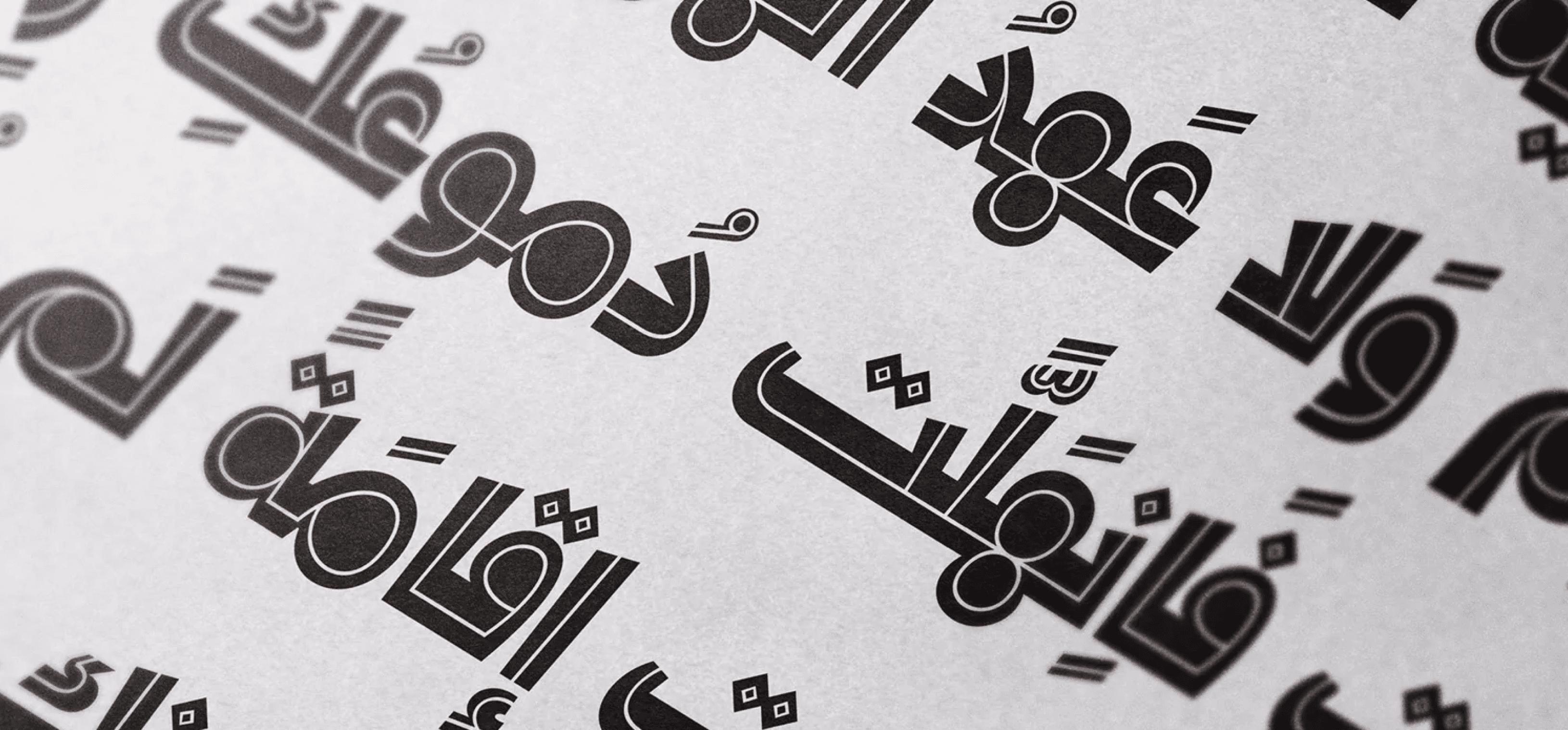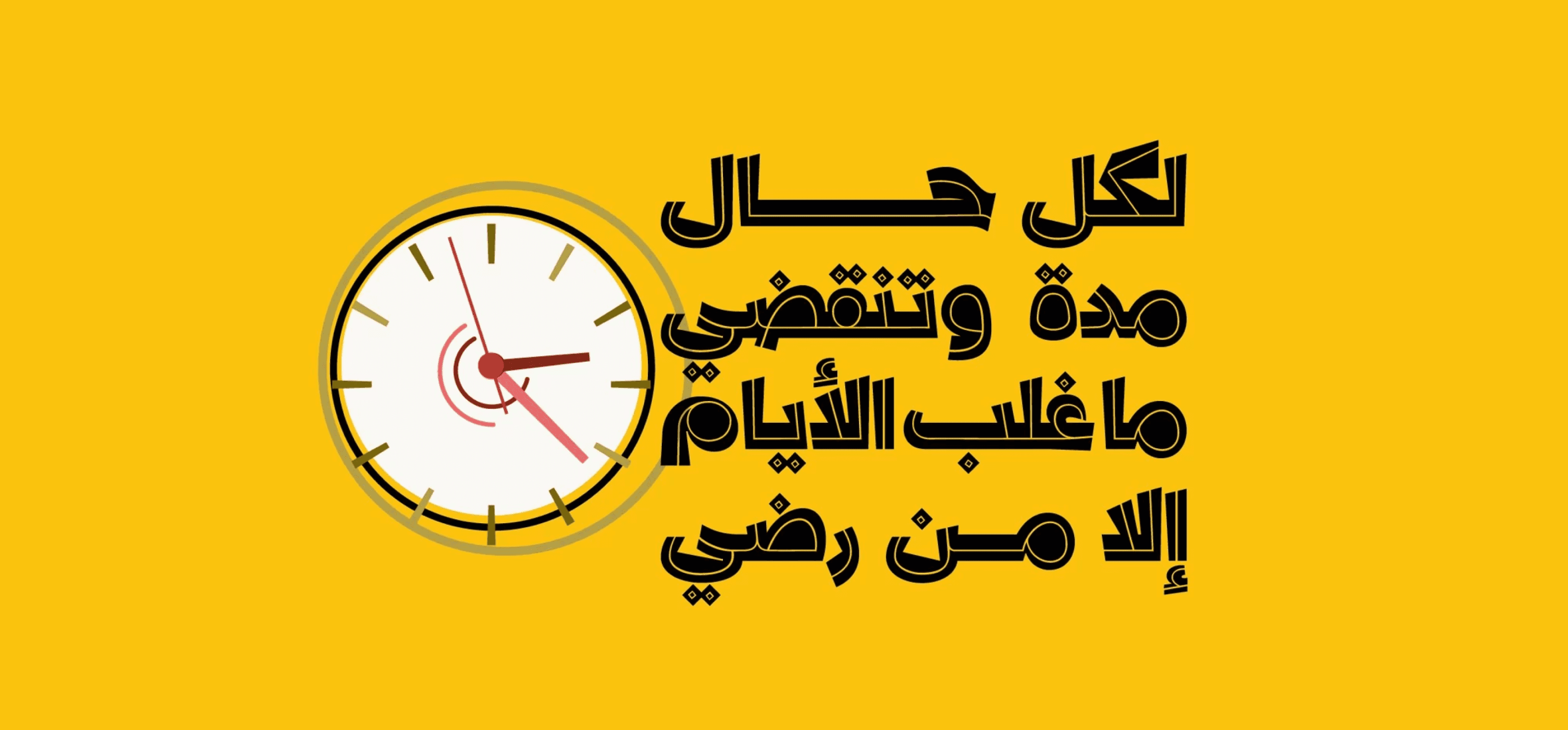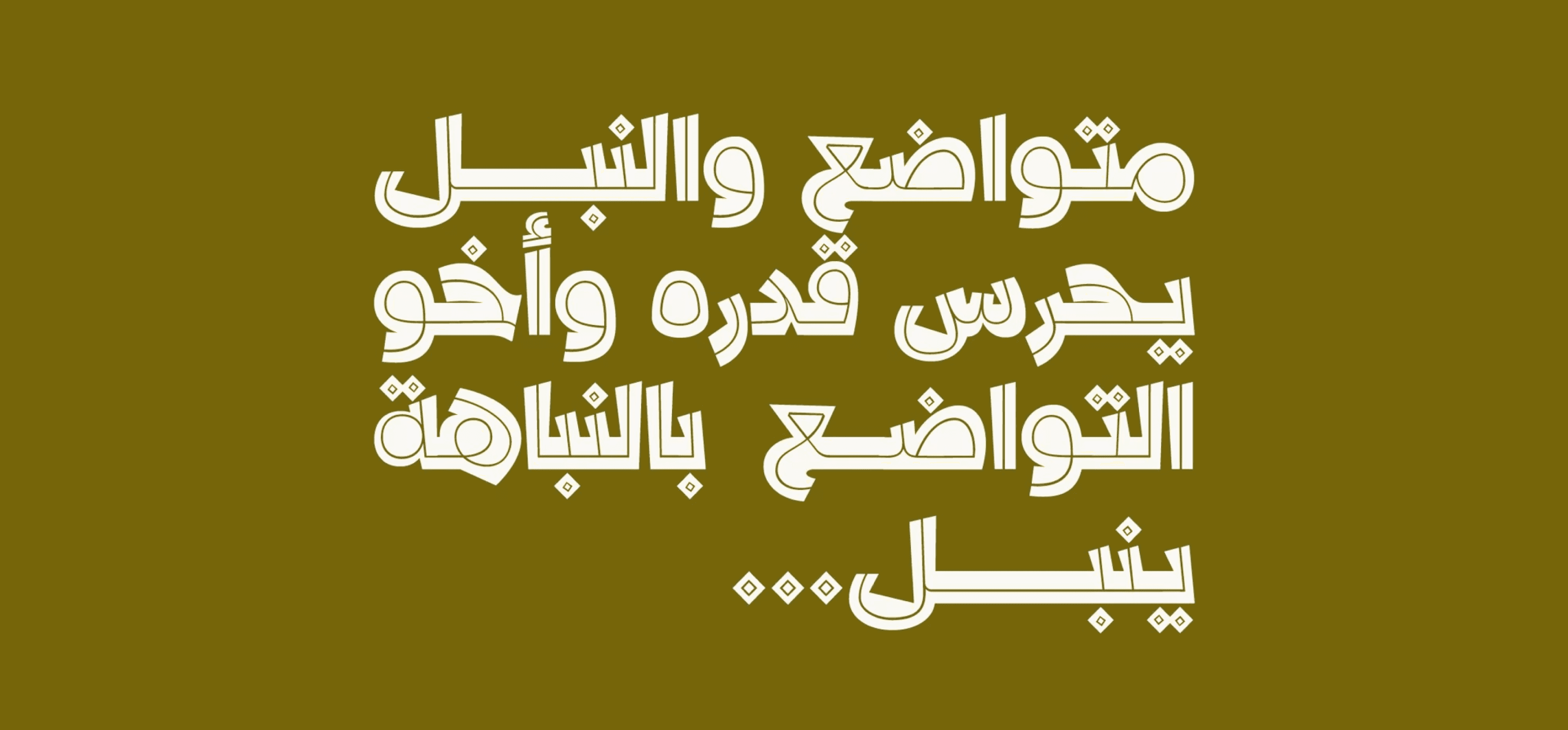
خط عربي فني مستوحى من الخط الكوفي المعاصر، يتميز بأشكاله الهندسية الحادة وتفاصيله الزخرفية الدقيقة.
مصمم ليمنح النصوص طابعًا جريئًا ومميزًا، ما يجعله مثاليًا للاستخدام في التصاميم الطباعية، الشعارات، والاقتباسات الملفتة.
Dardashah خيار مثالي للمشاريع التي تبحث عن حضور بصري قوي وهوية تصميمية استثنائية.